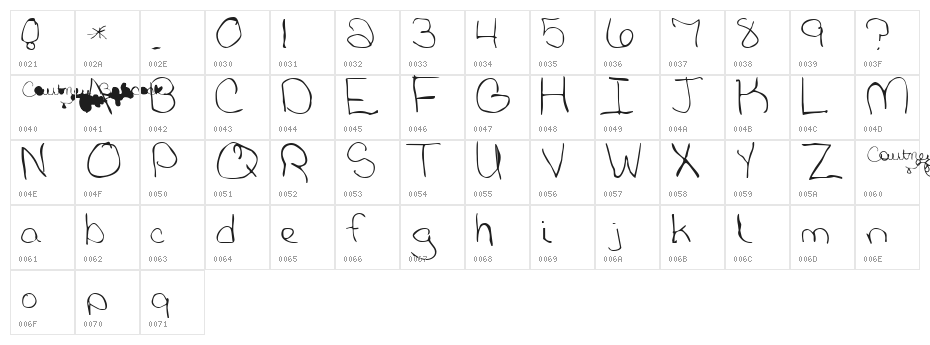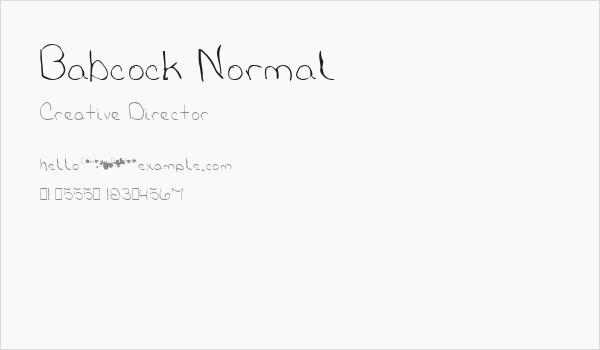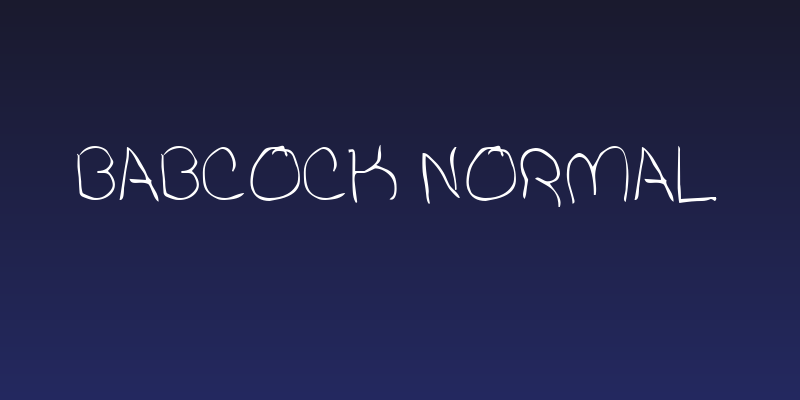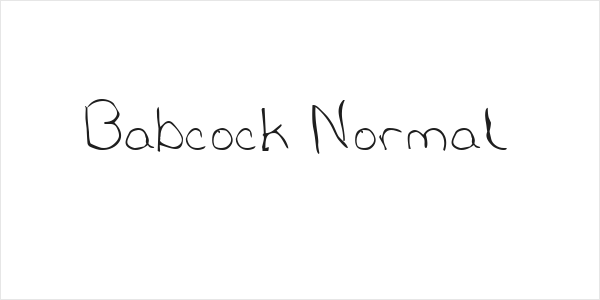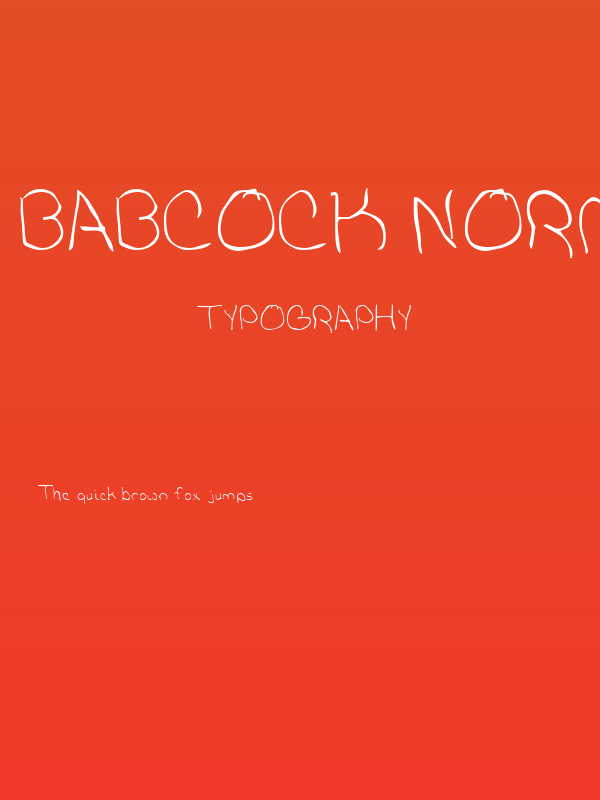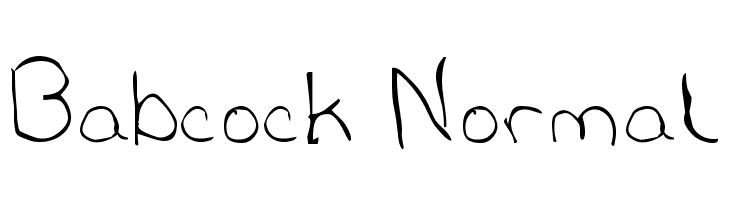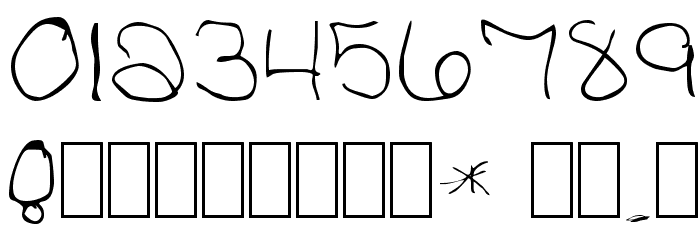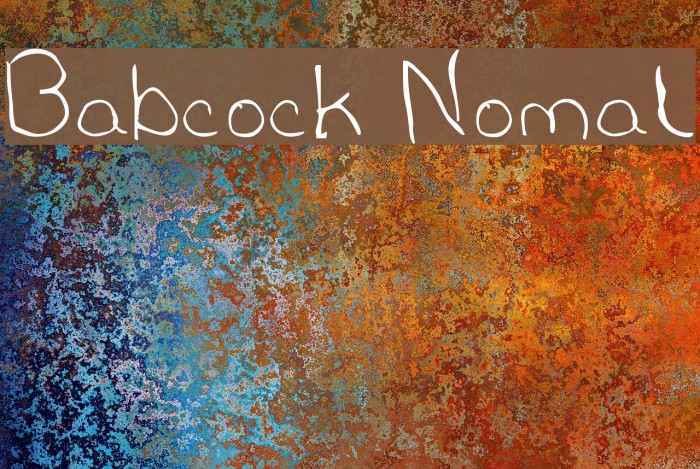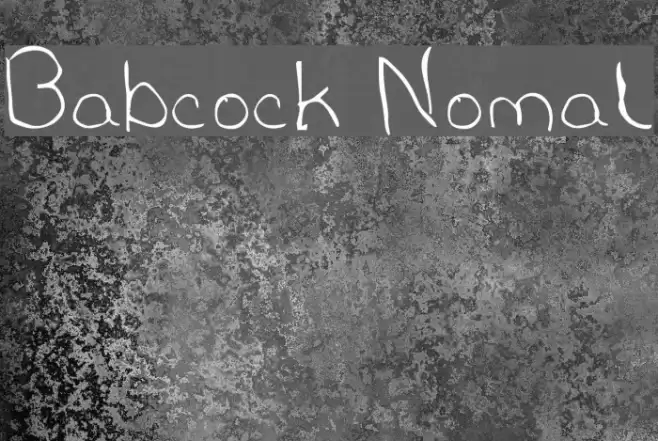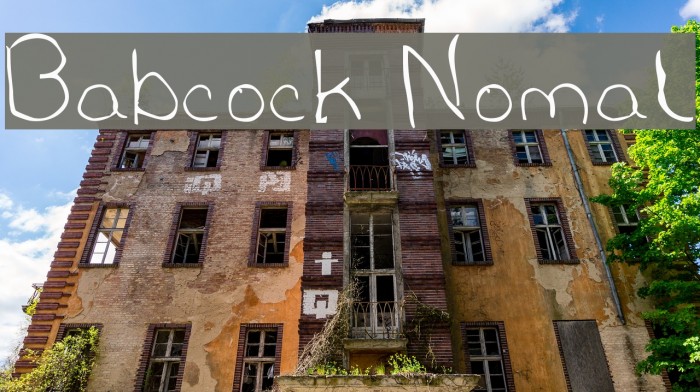
Babcock Normal Font
| Kategorien | Decorative |
| Gesamtstil | Casual |
| Anwendungsfall | Logos, Invitations, Creative projects |
| Vorgeschlagene Projekte | Ideal for greeting cards, children's books, creative posters, and personal branding. |